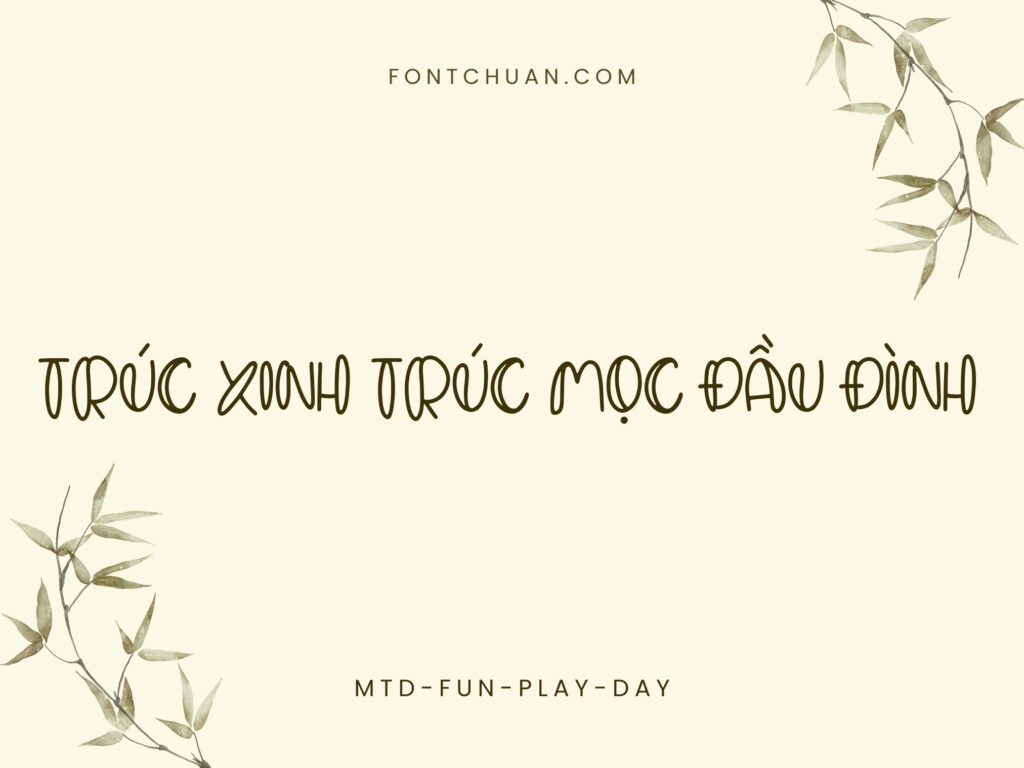
Font MTD Fun Play Day Việt Hóa
Font MTD Fun Play Day là một phông chữ sans-serif mang phong cách vui nhộn và thân thiện, được thiết kế với các đường nét đơn giản và dễ đọc. Font đã được Việt hóa bởi Mộc Hạ, hỗ trợ đầy đủ tiếng Việt cùng hơn 90 ngôn ngữ khác, mở rộng khả năng ứng dụng trong các thiết kế đa ngôn ngữ. Đây là một trong những phông chữ được cộng đồng thiết kế đánh giá cao và sử dụng trong nhiều dự án sáng tạo, đáp ứng nhu cầu đa dạng của người dùng.
MTD Fun Play Day nổi bật với thiết kế trẻ trung và năng động, mang đến cảm giác vui vẻ và thân thiện. Font rất phù hợp cho các thiết kế dành cho trẻ em, tiêu đề, bao bì sản phẩm, thiệp mời và các ấn phẩm đòi hỏi sự sáng tạo và cá nhân hóa. Các ngành nghề phù hợp bao gồm giáo dục, quảng cáo, công nghệ, thiệp cưới và ảnh cưới. Font này cũng lý tưởng cho các sự kiện như Tết, Giáng sinh, Valentine và các lễ hội khác.